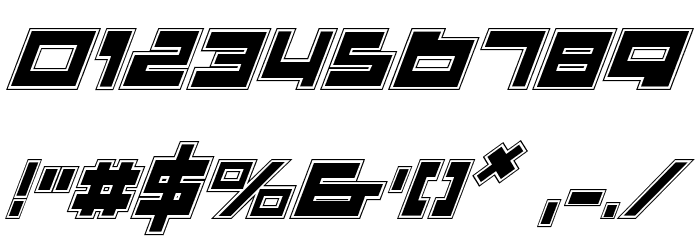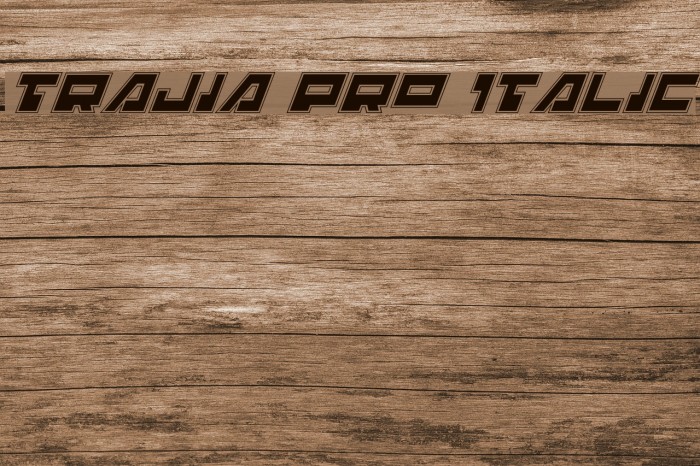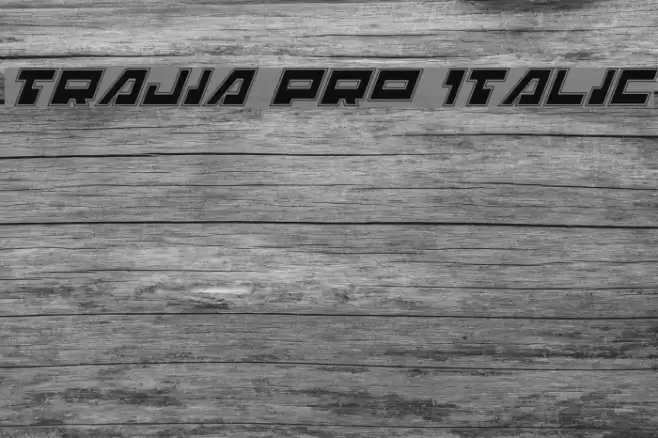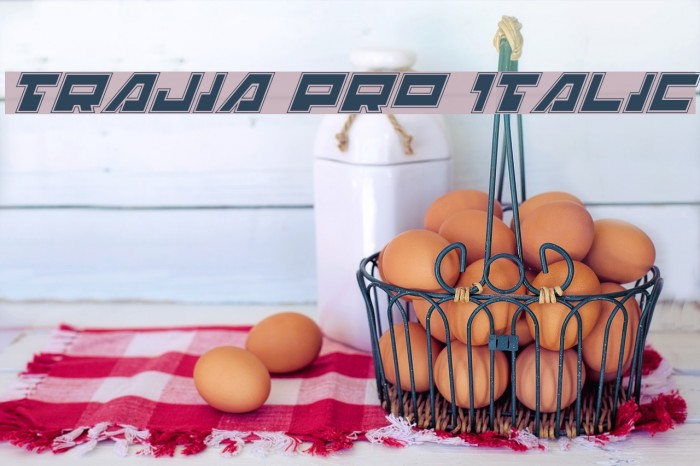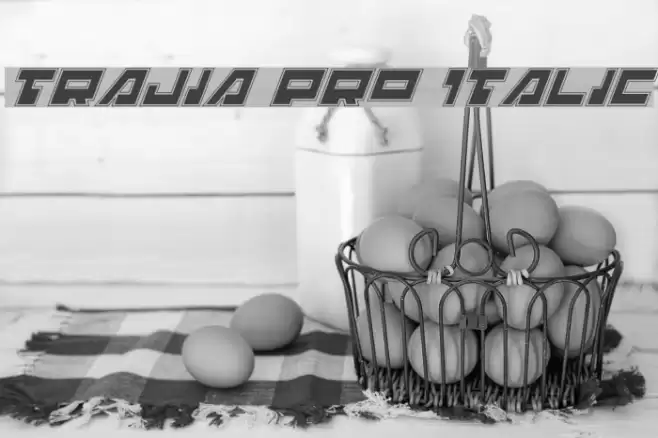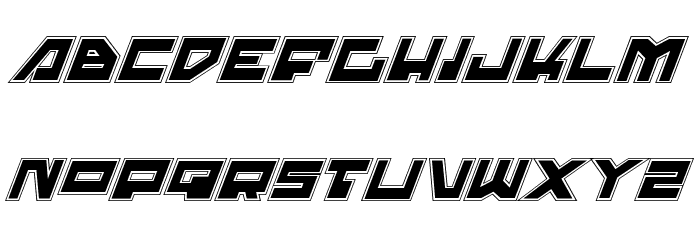
Trajia Pro Italic Font
✎ Sci-fi
| Vorgeschlagene Projekte | Ideal for sci-fi themed designs, tech company logos, video game titles, and dynamic posters. |